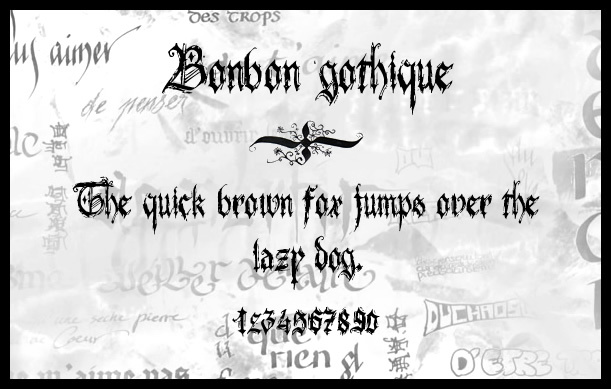
Bonbon Bleu to darmowy krój pisma w stylu gotyku średniowiecznego. Jego poszarpane kreski, faktura rozchlapanego atramentu i pęknięte krzywizny sprawiają wrażenie, jakby zostały wyrwane ze starej księgi zaklęć lub z pleców zniszczonej skórzanej kurtki. Litery wyglądają na porysowane i wyświechtane w idealny sposób, nadając nawet pojedynczym słowom surową, rytualną energię.
Bonbon Bleu świetnie sprawdzi się w projektach o mocnym klimacie: logo zespołów metalowych lub punkowych, plakatach horrorów, okładkach dark fantasy, tytułach gier, grafikach inspirowanych tatuażami czy ulotkach na Halloween. Ten darmowy font najlepiej wygląda w większych rozmiarach, gdzie jego ziarnista tekstura może w pełni wybrzmieć. Połącz go z prostym, geometrycznym krojem bezszeryfowym w tekście głównym, aby zachować czytelność, podczas gdy nagłówek będzie robił całe wrażenie.